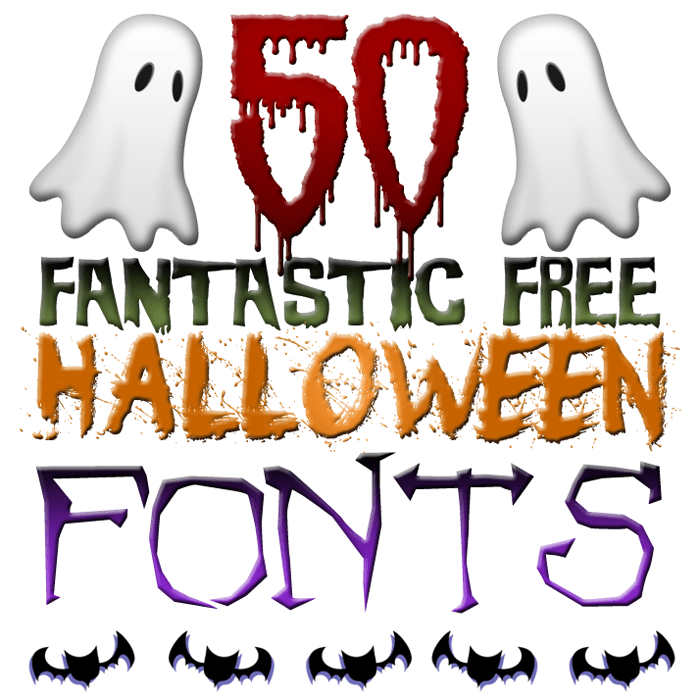
Хэллоуинских шрифтов в Google Docs
Хэллоуинские шрифты в Документах Google. Вы ищете идеальные шрифты для своего проекта на тему Хэллоуина? Не ищите ничего, кроме Google Docs! Благодаря множеству жутких и пугающих вариантов типографики вы можете добавить дополнительный слой навязчивой атмосферы к своим документам, слайдам и многому другому.
CREEPSTER
Creepster — это шрифт на тему Хэллоуина, доступный в Google Docs, созданный для создания жуткой и жуткой атмосферы. Шрифт имеет уникальный вид, нарисованный от руки, с зубчатыми краями и неровными штрихами, из-за чего он выглядит так, как будто он написан пером или ручкой. Creepster идеально подходит для создания плакатов, приглашений или флаеров на тему Хэллоуина, и он может добавить навязчивую нотку любому проекту. Это отличный вариант для тех, кто хочет добавить немного жуткого чутья своим документам или проектам. Разработано Сайдшоу.
EATER
Eater — уникальный дисплейный шрифт, зараженный темнейшей из редких болезней.
Этот шрифт не является обычным шрифтом, так как он имеет тревожную и жуткую ауру. Кажется, что шрифт медленно распространяется ночью, пока пользователь веб-шрифта спит, что делает его жутким и тревожным дополнением к любому дизайну или проекту. Болезнь, поразившая шрифт, кажется, живет своей собственной жизнью и проявляется в неровных краях, неровных линиях и искаженных формах букв. Eater идеально подходит для создания дизайна или графики, требующих пугающего и тревожного тона, и его можно использовать для создания плакатов на тему ужасов, обложек книг и других материалов. Шрифт не для слабонервных, так как он обязательно вызовет мурашки по спине. Так что, если вы ищете уникальный и пугающий шрифт, Eater может стать для вас идеальным выбором.
NOSIFER
Nosifer — это отличительный экранный шрифт, доступный в Google Fonts. Он имеет уникальный и смелый дизайн с толстыми неровными линиями, которые придают ему шероховатый, резкий вид. Шрифт идеально подходит для создания привлекающих внимание заголовков или заголовков, которые должны выделяться.
Он был вдохновлен работами немецких художников-экспрессионистов и часто ассоциируется с ужасами или темными темами из-за его зубчатого вида. Буквы в Nosifer неправильные и слегка искаженные, что придает им рисованный вид. Этот шрифт идеально подходит для дизайнеров, которые хотят добавить немного индивидуальности и остроты своим проектам. Кроме того, шрифт доступен как в обычном, так и в курсивном начертании, что делает его универсальным и подходящим для целого ряда дизайнерских приложений. В целом, Nosifer — это смелый и яркий шрифт, который обязательно сделает заявление в любом дизайне.
BUTHCERMAN
Butcherman — это экранный шрифт, который был преобразован в жуткий и ужасающий шрифт, вдохновленный темами зомби и ужасов. Шрифт выглядит так, как будто его взломали, нарезали и оставили умирать, но ему все же удается ползти, создавая жуткий и тревожный эффект. Буквы в «Бутчермане» неровные и шероховатые, напоминающие разорванный и изодранный лист бумаги.
Шрифт идеально подходит для создания дизайнов, требующих пугающего и ужасного вида, таких как плакаты на Хэллоуин, названия фильмов ужасов или обложки книг. Его смелый и неровный стиль добавляет уникальности и остроты любому проекту. Шрифт Butcherman универсален и может использоваться как для отображения, так и для основного текста, что делает его полезным дополнением к набору инструментов любого дизайнера. В целом, Butcherman — это шрифт, который обязательно произведет неизгладимое впечатление на любого, кто с ним столкнется.
Mystery Quest
«Mystery Quest» — это уникальный и интересный шрифт Google, который обладает таинственной и жуткой атмосферой. Это дисплейный шрифт со смелым и тяжелым дизайном с острыми краями и углами. Буквы расположены таким образом, что создается впечатление секретного кода или головоломки, ожидающей решения.
Шрифт выполнен в готическом стиле, напоминающем старинные рукописи и рукописные тексты. Он идеально подходит для дизайна на тему Хэллоуина, постеров фильмов ужасов и других проектов, требующих жуткого и таинственного прикосновения.
Шрифт имеет хорошую разборчивость и читаемость, что делает его пригодным для использования в больших размерах. Однако из-за своего уникального дизайна он может быть не лучшим выбором для длинных блоков текста или меньшего размера шрифта.
В целом, «Mystery Quest» — отличный шрифт для создания ощущения интриги и тайны в ваших дизайнерских проектах.
FRIJOLE
Frijole — это шрифт на тему Хэллоуина, доступный в Google Fonts. Это игривый и причудливый шрифт с жуткой и веселой атмосферой. Frijole — это рукописный шрифт, который идеально подходит для создания уникального и запоминающегося дизайна.
Шрифт имеет толстые и неровные штрихи, которые придают ему немного жуткий и жуткий вид. Его дизайн вдохновлен старинными постерами фильмов ужасов с яркими и стилизованными буквами. Шрифт имеет рукописный стиль, который добавляет индивидуальности любому проекту.
Frijole — это универсальный шрифт, который можно использовать для различных проектов, связанных с Хэллоуином, таких как приглашения на вечеринки, плакаты, листовки и многое другое.
Его игривый и забавный дизайн идеально подходит для того, чтобы добавить нотку жуткого юмора в ваш проект. Шрифт также легко читается, что делает его идеальным для заголовков и заголовков.
53. Жуткий Хэллоуин
Это уникальный дисплейный шрифт с достаточно жутким видом в духе Хэллоуина. Вы можете использовать шрифт Halloween Spooky практически для чего угодно, поскольку он включает в себя полный набор основных символов, строчные и прописные буквы, цифры, знаки препинания, лигатуры и иностранные глифы.